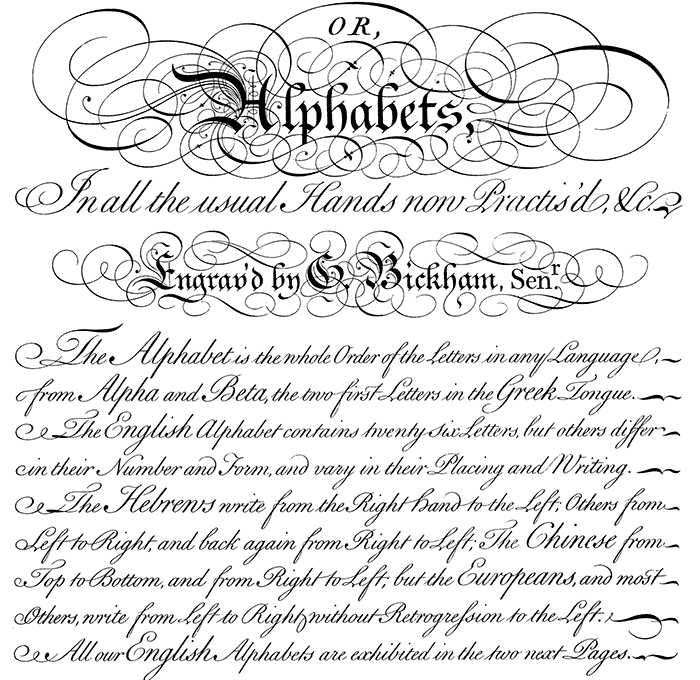
George Bickham der Ältere
George Bickham der Ältere (1684–1758) war ein englischer Schreibmeister und Graveur. Mit seinem Werk »The Universal Penman« prägte er die Gestalt der englischen Schreibschrift im 18. Jahrhundert.